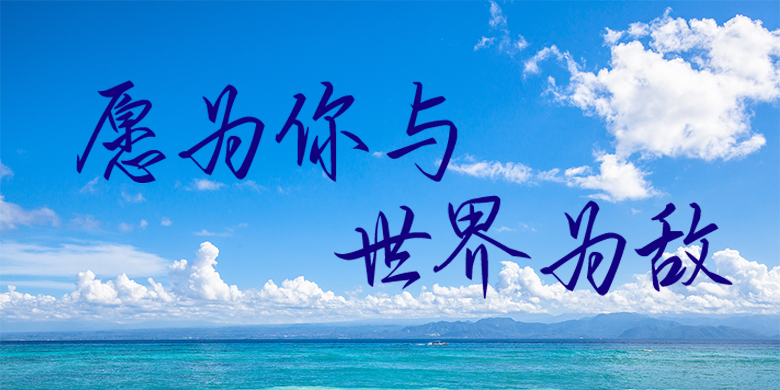
方正手迹-愿为你与世界为敌
方正手迹-愿为你与世界为敌,这款字体结构工整、笔画清晰,兼顾美观与易读性,适用于标题、正文、海报、包装、LOGO 等多种场景。字形优雅稳定,风格百搭耐看,适配日常排版与创意设计,让文字呈现更舒适、更具质感。方正手迹-愿为你与世界为敌一笔一画,皆是细节,以均衡的比例、流畅的线条打造舒适视觉体验,字形端正大气,风格简约现代。无论是商业设计、品牌宣传还是日常排版,都能轻松驾驭,让文字更有格调与力量。方正手迹-愿为你与世界为敌字体下载。
这款体行笔劲健爽利,锋芒毕露,洒脱飘逸,具有很强的视觉冲击。而字形娟秀隽永,中宫收紧,结字严谨,承自传统书法,格调高雅又不失现代感。适用于现代诗歌、短文的排版以及文化、商业类品牌的广告语设计。